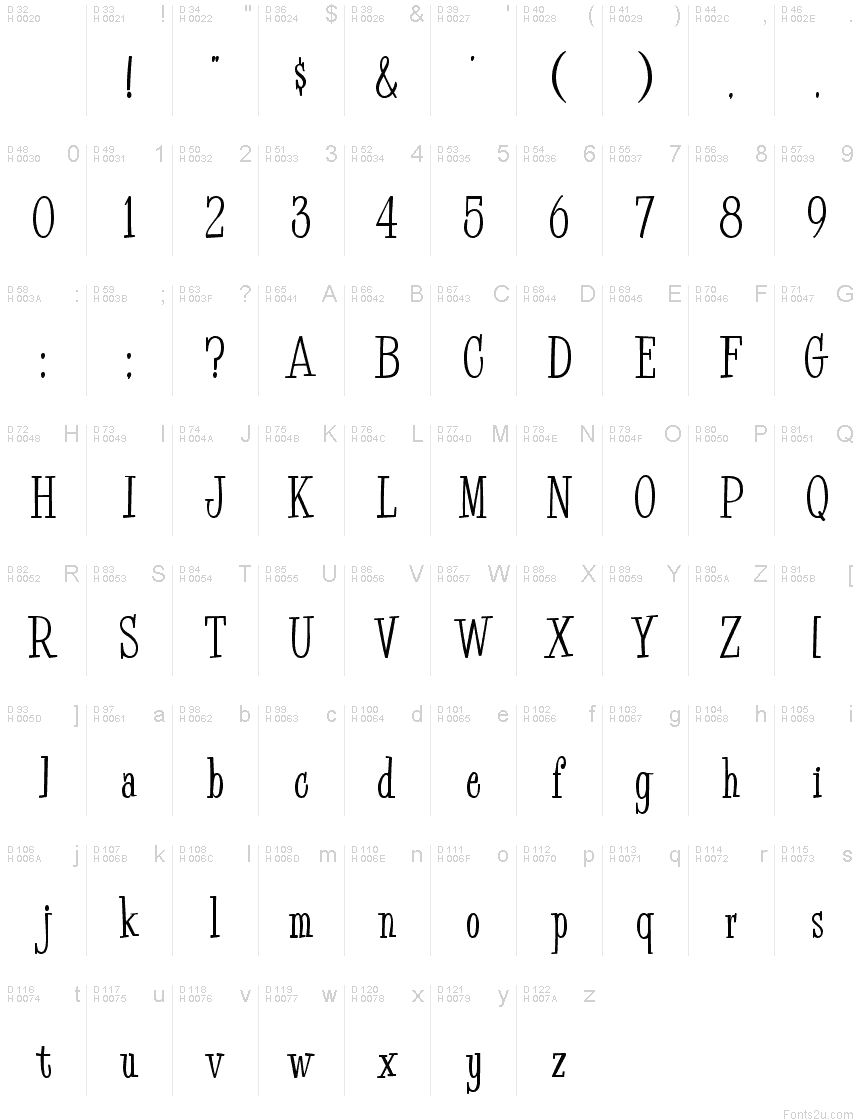
Krój Bud Easy autorstwa Johna D. Banksa wyróżnia się wysokim, nieszablonowym stylem szeryfowym, wąskimi literami i swobodnym, ręcznie kreślonym rytmem. Kreska pozostaje czysta i pionowa, dzięki czemu tekst jest czytelny, zachowując jednocześnie luźny charakter. Ten darmowy font świetnie sprawdzi się w zaproszeniach, radosnych plakatach, menu kawiarnianym, opakowaniach handmade oraz przyjaznych logo.
Ustaw Bud Easy w nieco większym rozmiarze, aby jej smukłe kształty i luźne światła mogły wybrzmieć, a w przypadku dłuższych tekstów zestaw ją z prostym krojem bezszeryfowym. Ten darmowy font doskonale nadaje się również do tytułów książek dla dzieci, grafik z cytatami i prac scrapbookingowych, które mają być ciepłe, ale nie przeładowane.
Bud Easy